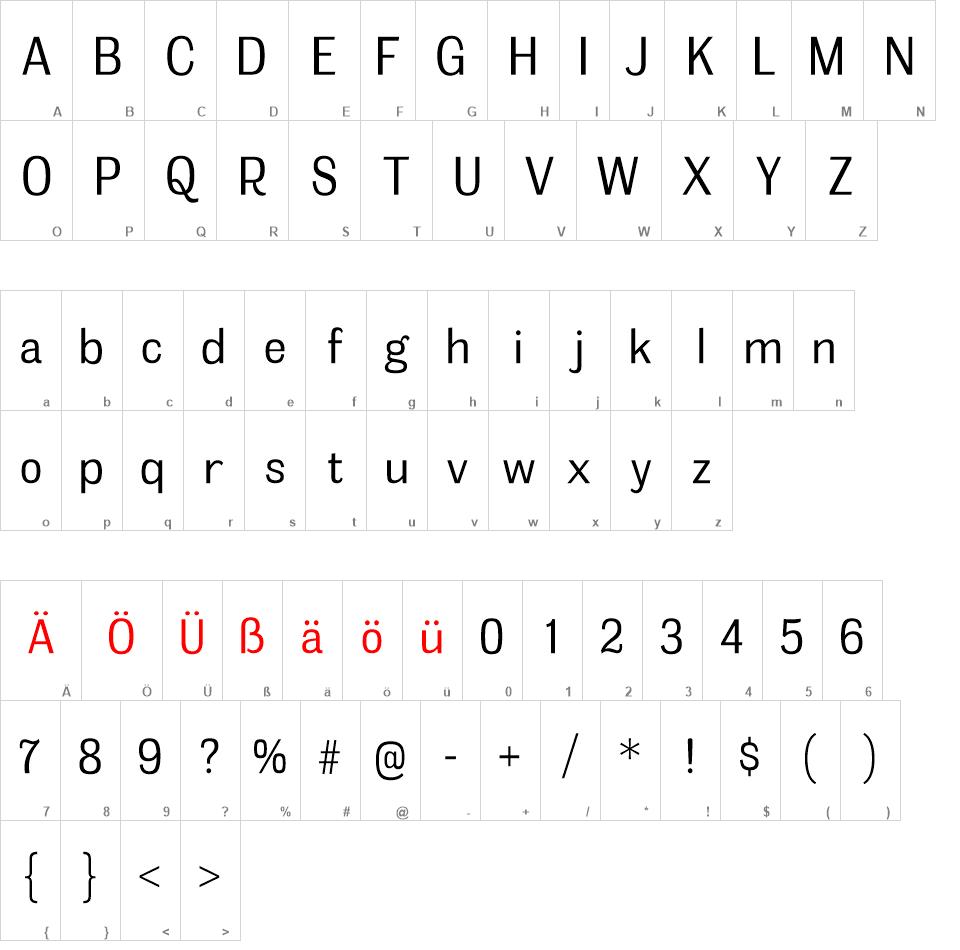
Meloche Font
Meloche ist ein einzigartiger, grotesker Sans Serif-Stil, der Ende des 19. Jahrhunderts von handgemalten französischen Zeichen beeinflusst wurde. Es liegt zwischen 7 Gewicht und Kurve. Zu den OpenType-Funktionen gehören numerische Ordinalzahlen, Brüche, Nummern im alten Stil und ein einfaches Q. In OpenType-fähigen Anwendungen können Sie auf das 20 gewichtsangepasste Fleur-de-Lis-Symbol zugreifen, indem Sie die Funktionscodes [fleur1] [fleur2] [fleur3] eingeben. Meloche ist Griechisch, Vietnamesisch, Kyrillisch, Pan-Nigerianisch und unterstützt fast alle lateinischen Sprachen.